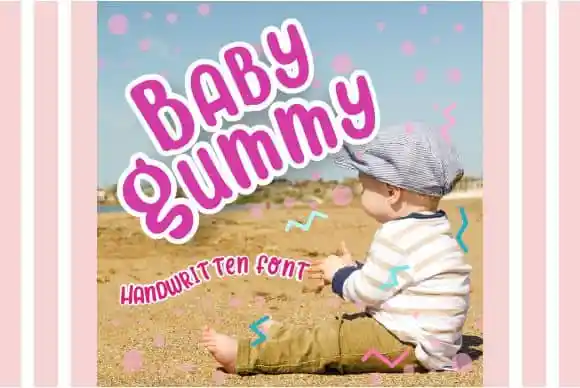
Baby Gummy Display Font – Download Grátis
Baby Gummy Display Font é uma fonte de exibição encantadora e peculiar, ideal para adicionar uma sensação leve e alegre a qualquer design. Esta fonte está concebida especialmente para criar visualizações criativas e divertidas, que destacam seu trabalho ao mesmo tempo em que adiciona um toque carinhoso. Como designer Aldi Wangsadipa mencionou na descrição original, o Baby Gummy Display Font é uma escolha ótima para adicionar beleza aos seus projetos de design, seja ele para rótulos de lanches, materiais educacionais ou até mesmo como fonte principal em um site. Essa fonte traz alegria e um toque descontraído que certamente fará seus trabalhos se destacarem ainda mais do seu público. Com Baby Gummy Display Font, você pode transformar qualquer conceito criativo em algo realmente único e encantador.